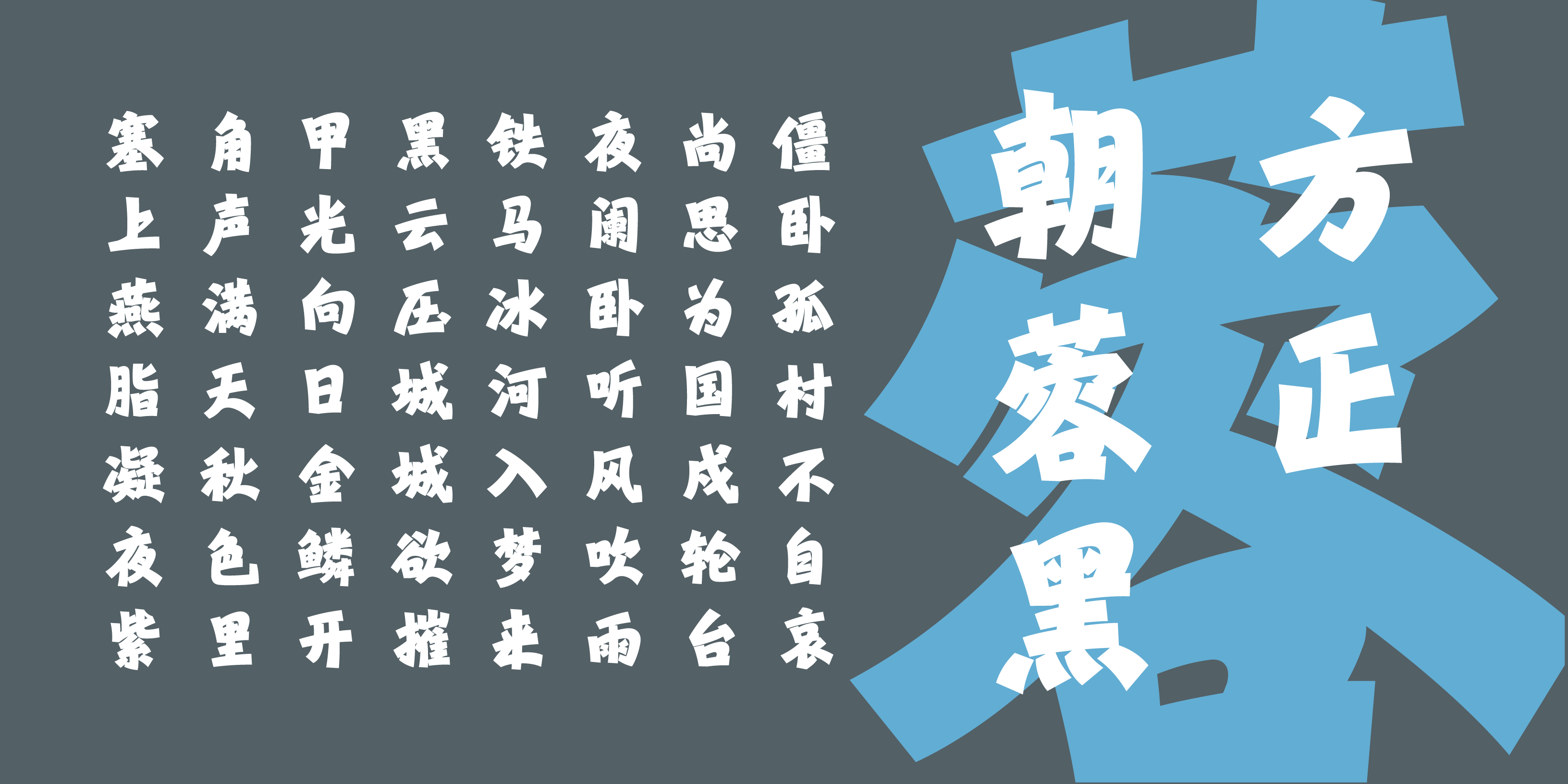
方正朝蓉黑
日出扶桑一丈高
读书求学不宜懒,天地日月比人忙。
燕语莺歌希领悟,桃红李白写文章。
这款字是第12届方正奖评委奖作品。行楷与黑体的融合,参考行书的运笔方式用黑体生硬的形式表达。字形大气磅礴,刚柔并济,既有行书的行云流水,也有黑体的简洁与现代感,有笨拙亦有灵动,又具备碑刻的稳重硬朗,字形粗犷有力,朝”即朝阳、朝气,寓意着活力和生机;“蓉”指秀美、娇艳之义,寓意秀美、灵巧的特点,适用于标题、海报等。